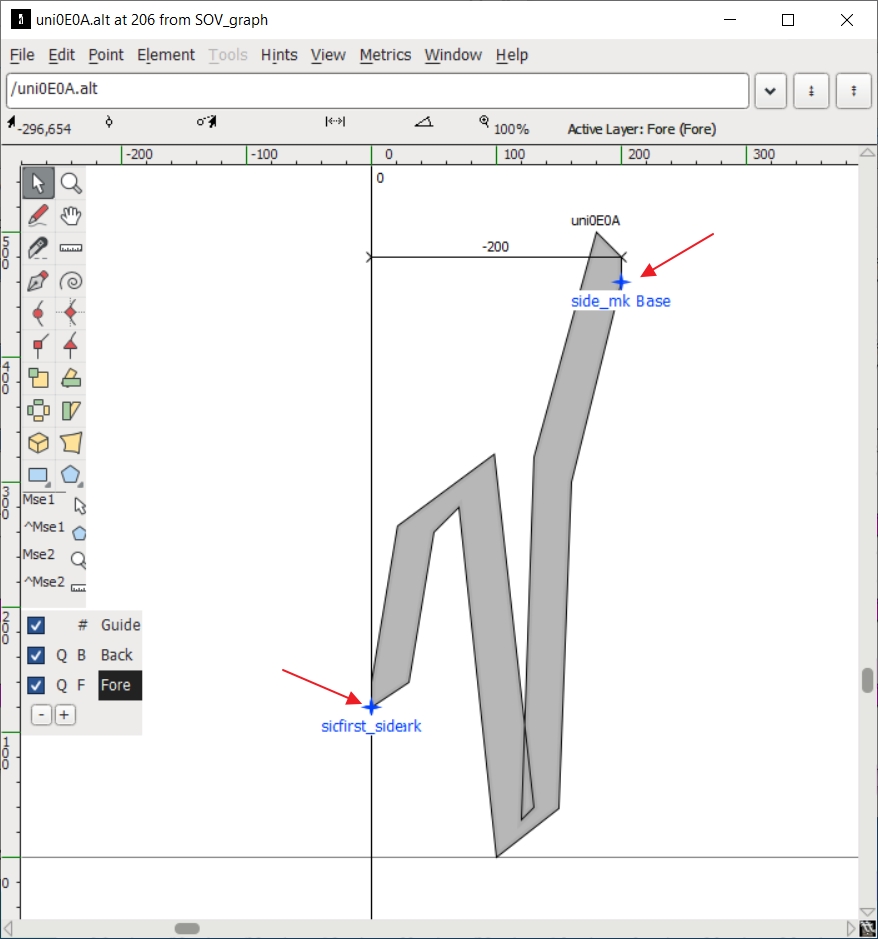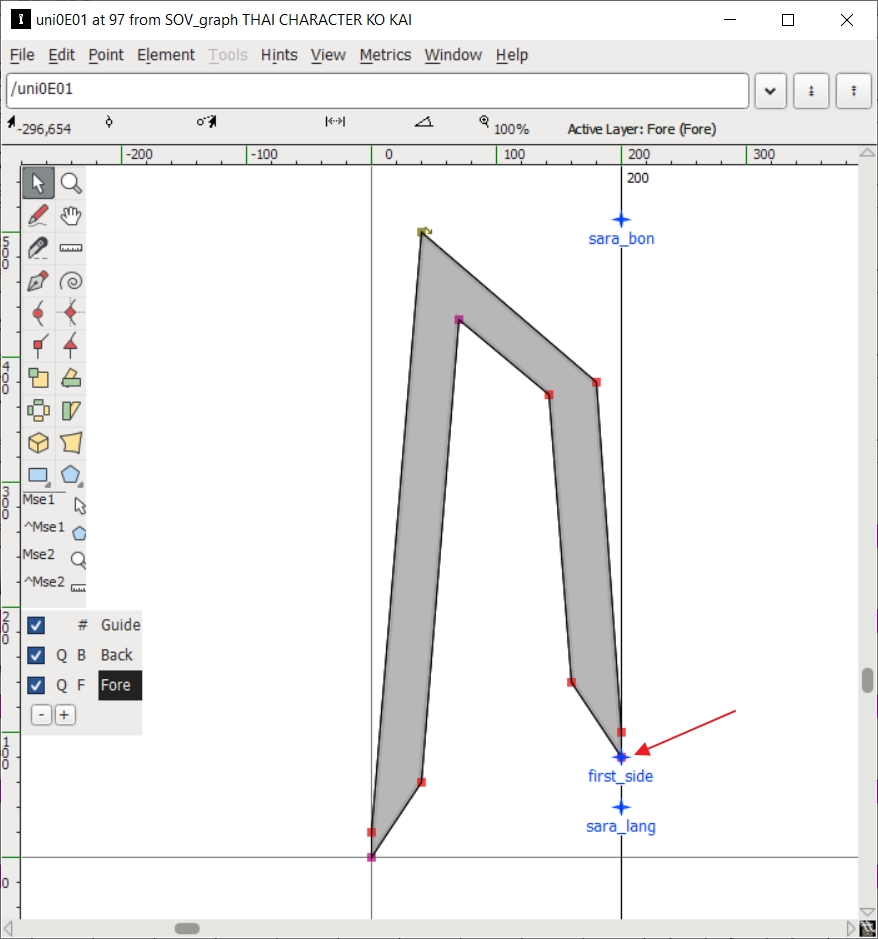
ทำฟอนต์กราฟ
ฟอนต์กราฟ ตัวอักษรปลายอักษรต่อกับต้นตัวอักษรถัดไป ขึ้นหรือลงขึ้นกับตัวอักษรนั้นๆ ดังนั้นกราฟจะเป็นรูปแบบไหน ขึ้นกับคำที่พิมพ์ลงไป ไม่แน่นอน และสามารถพุ่งทะลุบรรทัดได้  .. ทั้งหมดนี้คุณสมบัติ แล้วก็เป็นโจทย์ของฟอนต์ตัวนี้
ยังนึกการเอาใช้งานแบบอื่นไม่ได้เหมือนกัน แต่อยากบันทึกเทคนิคเอาไว้ เผื่อเป็นประโยชน์ในภายหน้า
1. เทคนิคสำคัญคือ ทำอักษรอีกชุดนึงขึ้นมา หน้าตาเหมือนกับตัวอักษร แต่กำหนดให้เป็นสระวรรณยุกต์ (ที่มีแถบสีชมพูทั้งหมด)
2. ตัวอย่าง คุณสมัติของ ก.ไก่ 2 ตัวนี้คือ ตัวแรกเป็น พยัญชนะ  ตัวที่สองเป็น สระวรรณยุกต์
3. ตัวพยัญชนะ นอกจากกำหนด mark สระบน ล่าง แล้วให้เพิ่ม สระข้าง ขึ้นมา(ลูกศรชี้ first_side)
4. ส่วนตัวสระวรรณยุกต์ มี mark 1 จุด mark on mark 2 จุด
4.1 mark สระข้าง  เพื่อเชื่อพยัญชนะตัวแรก (first_side Mark)
4.2 mark on mark สระข้าง mark เพื่อเชื่อมสระตัวถัดไป (ลูกศรชี้ side_mk Mark)
4.3 mark on mark สระข้าง base เพื่อกำหนดตำแหน่งเชื่อมสระตัวถัดไป (ลูกศรชี้ side_mk Base)
4.4 ตำแหน่ง mark จะเปลี่ยนไปตามรูปอักษร
5. เขียน script กำหนดให้ อักษรตัวแรกเป็นพยัญชนะ ที่เหลือเป็นสระวรรณยุกต์ให้หมด
5.1 เมื่อพิมพ์อักษรตัวแรก จะเหมือนปรกติ
5.2 แต่เมื่อพิมพ์อักษรตัวที่สอง อักษรจะเลื่อนตำแหน่งขึ้นลงมาที่ mark ข้างของอักษรตัวแรก
5.3 แต่เมื่อพิมพ์อักษรตัวถัดๆไป อักษรจะเลื่อนตำแหน่งขึ้นลงมาที่ mark on mark ของอักษรตัวก่อนหน้า เสมอ
เส้นอักษรก็จะเชื่อมต่อเนื่องขึ้นลงไปมา..ตามตัวอักษรที่พิมพ์ลงไป
ปล. ภาษาไทย ไม่แพ้ใครในโลก ระดับความยาก up level ขึ้นมาอีก เนื่องจากตัวอักษร(ที่ทำหน้าที่เป็นสระตอนนี้)ดันมีสระบนล่างและวรรณยุกต์ ซ้อนเข้าไปอีก ..แน่นอน!!เราหลอกระบบไปรอบนึงแล้วโดยการเอาพยัญชนะมาทำเป็นสระ ดังนั้นมันไม่มีระบบสระจริงซ้อนสระปลอมที่เราทำไว้  จึงต้องทำการหลอกซ้อนหลอกเข้าอีกทีดังนี้
6. สร้าง ชุดสระบนล่าง อีกหลายชุด
6.1 ทำให้เป็นพยัชนะที่ไม่มีความกว้าง โดย ที่ตำแหน่งของ side_mk Mark และ side_mk Base ไว้ตำแหน่งเดียวกัน
6.2 ตำแหน่งของ side_mk แต่ละชุด สูงต่ำ ไม่เท่ากัน ขึ้นอยู่กับว่า จะใช้กับพยัญชนะ ตัวใด เช่น ก.ไก่ side_mk อยู่ล่างๆ ช.ช้าง side_mk อยู่บนๆ
6.3 เขียน scirpt จับคู่ พยัญชนะ กับชุดสระ ให้เข้าคู่กัน สระไม่ลอยไม่จมเกินไป
เป็นอันจบงานได้
7. แถมท้ายด้วย การทำ space ที่มีความกว้างเท่าจำนวนอักษรที่พิมพ์ลงไป
- เนื่องจาก สระวรรณยุกต์ ไม่สามารถมีความกว้างได้ ดังนั้น เมื่อพิมพ์ไป 1 คำ แล้วเว้นวรรค พิมพ์คำถัดไป อักษรจะทับกันมั่วไปหมด
- จึงเขียน script ให้นับจำนวนตัวอักษรที่พิมพ์ แล้วเว้นระยะให้ตามจำนวนตัวอักษร
-  แต่ก็ไม่สามารถแม่นยำ แม้จะโกงโดยวิธี fix width ตัวอักษรไว้แล้ว แต่ภาษาไทยดันมีสระบนล่าง ทำให้ space ที่คำนวณให้เกินไปตามจำนวนสระบนล่างในคำ หรือประโยคนั้นๆจ้า
จบละ
anchor mark ที่ใช้นี่
ก็เป็นชนิดเดียวกับที่ใช้กับพวกสระวรรณยุกต์บนล่างเลยใช่ไหมครับ
แค่เปลี่ยนเป็นใช้กับตัวข้างๆ แทน
ถ้าแบบนี้เราก็สามารถเขียนเป็นฟอนต์ตัวเขียนติดๆ กันแบบ calligraphy ขึ้นๆ ลงๆ ได้เลย :25: